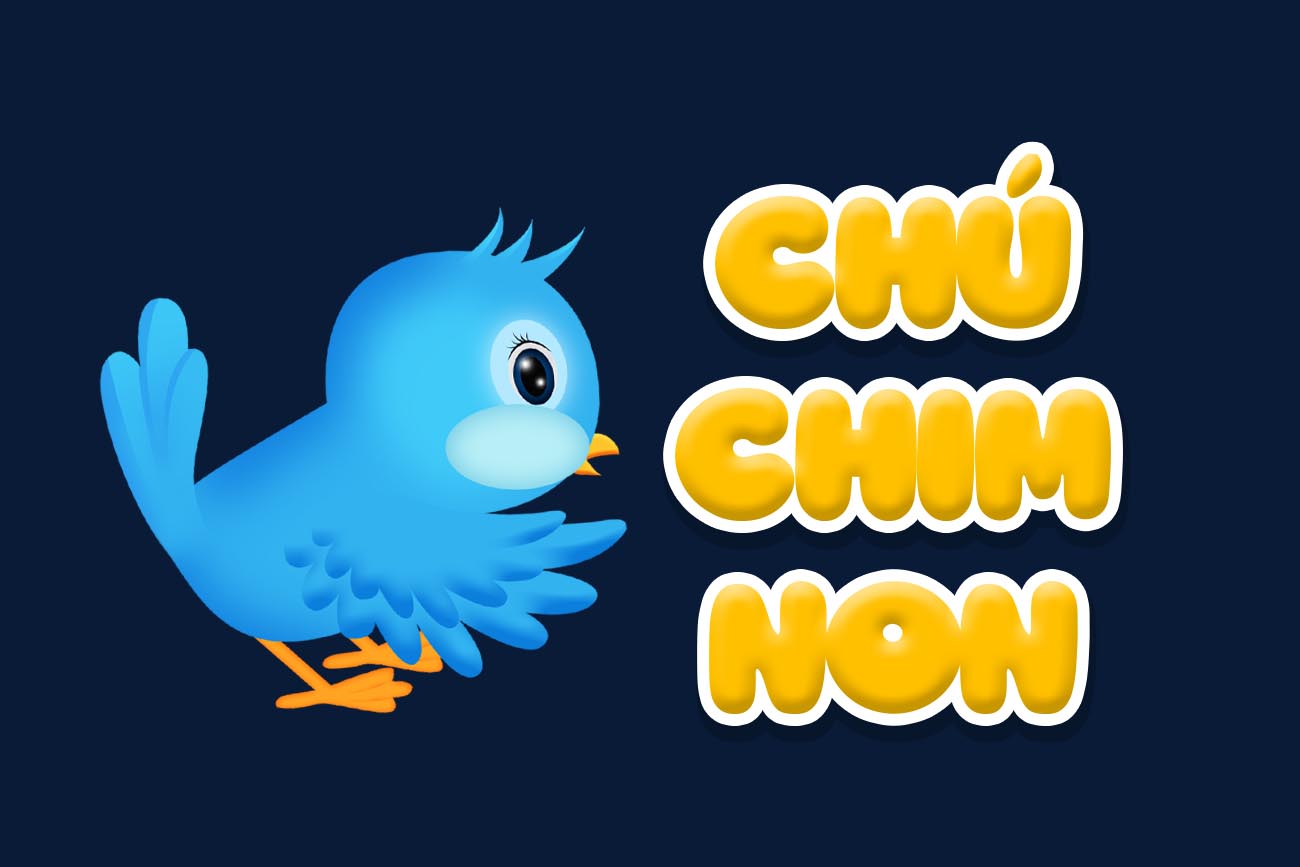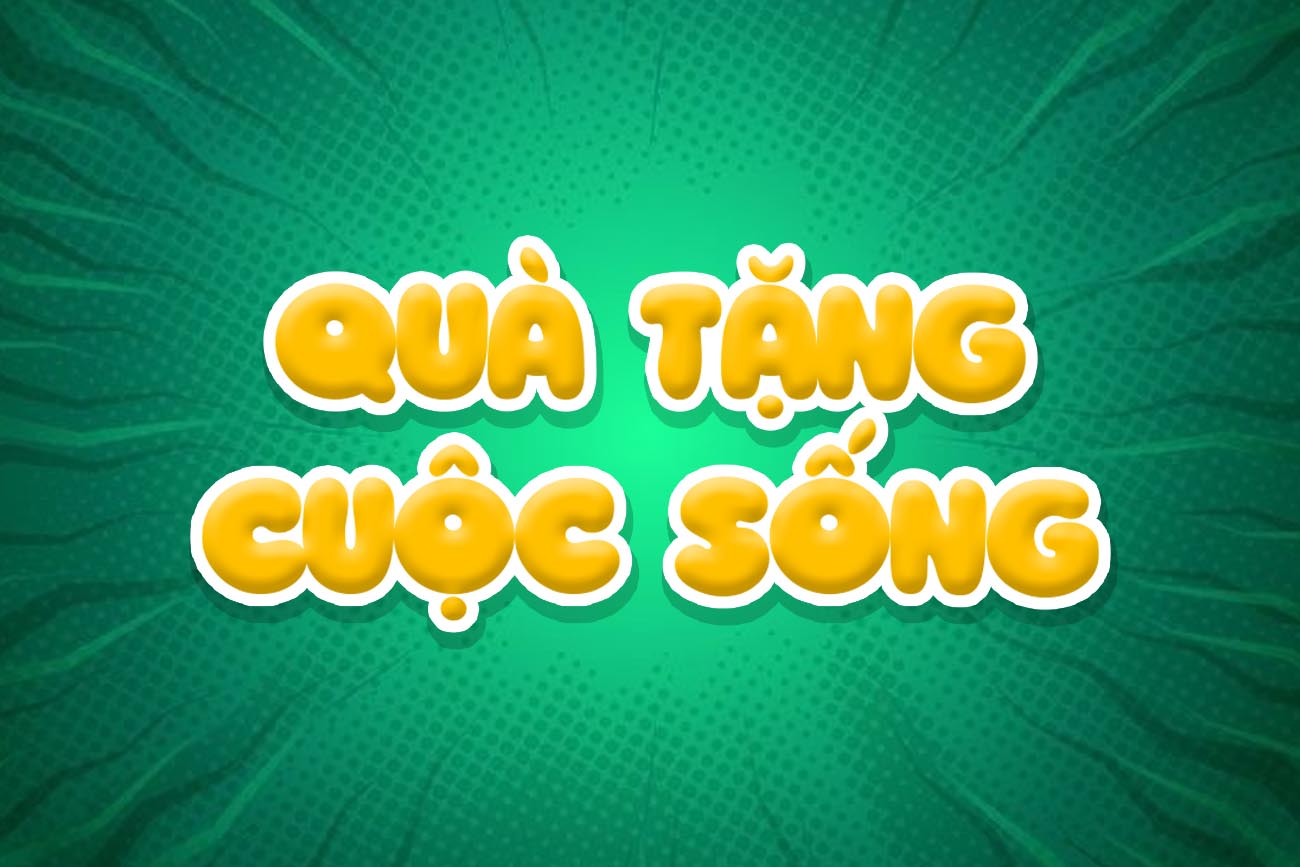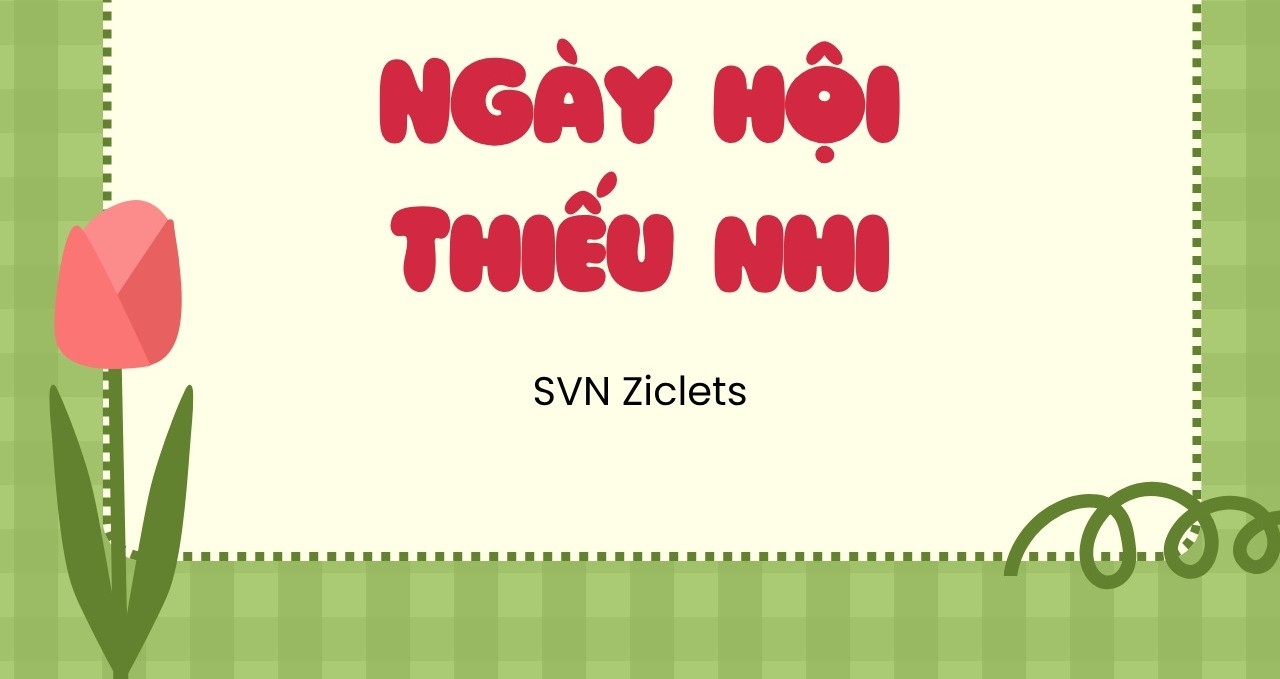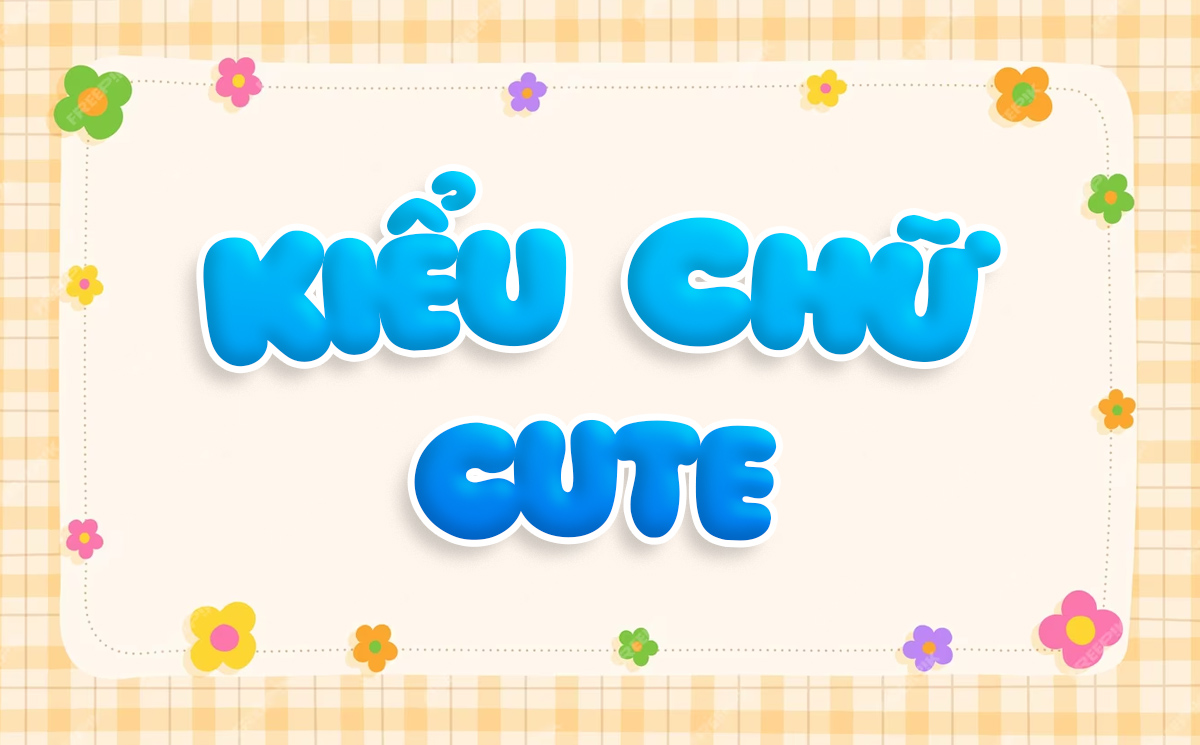
SVN Ziclets là bộ phông chữ thuộc dòng Display mang phong cách hoạt hình Retro vui nhộn, ngộ nghĩnh và tràn đầy sự phá cách ngẫu hứng. Được sáng tạo bởi nhà thiết kế David Kerkhoff (Hanoded) và được đội ngũ SVN tinh chỉnh hoàn thiện hệ thống dấu tiếng Việt, Ziclets là lựa chọn tuyệt vời cho các thiết kế bao bì bánh kẹo, kẹo cao su, poster sự kiện thiếu nhi và các ấn phẩm dành cho giới trẻ yêu thích sự độc lạ. Doozypack.vn cung cấp link SVN Ziclets Download chuẩn kỹ thuật, giúp bạn sở hữu phông chữ hoạt hình đặc sắc mà không lo gặp bất kỳ lỗi hiển thị dấu thanh nào khi thiết kế in ấn.
Đặc điểm thẩm mỹ độc đáo của bộ font SVN Ziclets
Ziclets không đi theo quy chuẩn ngay ngắn của các phông chữ hình học; nó chinh phục người xem nhờ sự méo mó có chủ đích, mô phỏng lại những nét vẽ tay trong các bộ phim hoạt hình kinh điển thế kỷ 20.
Phong cách hoạt hình Retro ngộ nghĩnh và đầy ngẫu hứng
Đặc trưng lớn nhất của SVN Ziclets là các con chữ có hình khối góc cạnh tự nhiên, không đều nhau như được cắt ghép thủ công bằng kéo. Nét chữ có độ dày dặn vừa phải, các đường nét xiêu vẹo nhẹ nhàng tạo nên một cảm giác hài hước, dí dỏm và cực kỳ lôi cuốn. Khi đặt Ziclets làm tiêu đề trên bao bì, thương hiệu của bạn sẽ ngay lập tức lan tỏa năng lượng vui vẻ, kích thích trí tò mò và sự thích thú của khách hàng, đặc biệt là các bạn nhỏ.
Cấu trúc chữ nhấp nhô vui nhộn và giàu biểu cảm
Các ký tự của Ziclets sở hữu đường chân chữ (baseline) nhấp nhô không theo một đường thẳng cố định, tạo nên nhịp điệu Typography như một điệu nhảy vui nhộn. Phong cách này mang lại sự tự do tuyệt đối, giúp bản thiết kế thoát khỏi cảm giác khuôn mẫu khô cứng, cực kỳ ăn ý với các dòng sản phẩm đồ ăn vặt, nước giải khát mùa hè hoặc các phụ kiện thời trang đường phố độc lạ.
Ưu điểm nổi bật của bản font SVN Ziclets Việt hóa
Khi ứng dụng các phông chữ hoạt hình ngẫu hứng vào thị trường trong nước, sự chỉn chu về dấu câu là yếu tố quyết định đến tính thẩm mỹ của ấn phẩm:
- Khắc phục triệt để lỗi dấu tiếng Việt: Phiên bản tải font SVN Ziclets Việt hóa đã được đội ngũ thiết kế trau chuốt thủ công từng dấu câu. Các dấu sắc, huyền, hỏi, ngã, nặng được vẽ với phong cách ngộ nghĩnh đồng điệu cùng thân chữ gốc, không gây cảm giác chắp vá hay đè nét làm mất tính thẩm mỹ.
- Bảo đảm tính đồng nhất thương hiệu: Việc tải font Việt hóa SVN Ziclets chuẩn giúp bạn tự tin dàn trang tiêu đề tiếng Việt mà không lo hiện tượng lỗi ô vuông hay nhảy về font hệ thống khô khan.
03 Ứng dụng thực tế của font SVN Ziclets trong sản xuất bao bì
- Bao bì Kẹo cao su & Bánh kẹo trẻ em: Tiêu đề thương hiệu in bằng font Ziclets kết hợp cùng màu sắc tươi sáng tạo nên vẻ ngoài vui tươi, kích thích sự hào hứng của các bé.
- Hộp giấy đồ ăn vặt (Snacks, Khô gà, Bỏng ngô): Nét chữ méo mó dí dỏm gợi cảm giác món ăn giòn tan, vui nhộn và đậm chất đường phố.
- Tem nhãn dán Sticker & Nhãn chai đồ uống: Cấu trúc chữ phá cách rất thích hợp để in các tem decal tròn hoặc tem niêm phong hộp hàng, giúp sản phẩm trông sinh động và trẻ trung hơn.
03 Lưu ý kỹ thuật khi in ấn với phông chữ hoạt hình phá cách Ziclets
- Kiểm soát khoảng cách dòng (Leading): Do các ký tự của Ziclets có độ cao nhấp nhô không đều, bạn nên căn chỉnh khoảng cách giữa các dòng chữ thủ công để tránh tình trạng các dấu thanh của dòng dưới chạm vào chân chữ của dòng trên.
- Lựa chọn hệ màu sắc tương phản cao: Phong cách Ziclets đẹp nhất khi phối cùng các tông màu rực rỡ (vàng chanh, cam sáng, xanh neon). Bạn có thể thêm một đường viền (Stroke) đậm màu đen quanh chữ để tiêu đề nổi bật rõ ràng trên các nền hình ảnh phức tạp.